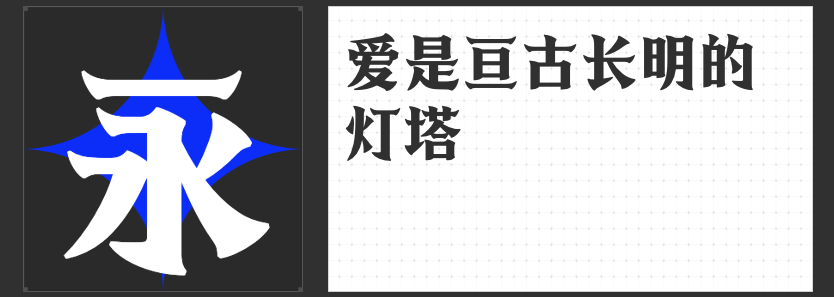
中秋佳节,让传统与现代交融的四款字体推荐
中秋佳节,自古以来便是中国人团圆美满的重要象征,也是展示传统文化魅力的最佳时刻。在这个特殊的节日里,选择一款既能体现传统韵味又能兼顾现代审美的字体,对于宣传设计来说至关重要。以下是四款适合用于中秋节宣传设计的字库字体推荐,每款字体都独具特色,适用于不同的设计用途。
1.造字侠热辣隶简
隶书作为一种历史悠久的汉字书写风格,以其工整中带有变化的特点著称。造字侠热辣隶简则是在传统隶书基础上加入了更多现代元素,使其更符合当今审美趋势。这种字体非常适合用于中秋节活动的邀请函、海报以及各种宣传材料的设计。无论是制作一张充满节日气氛的贺卡,还是一张吸引眼球的广告牌,热辣隶简都能以其独特的韵味增强作品的文化内涵。
2.造字侠朝凤宋简
宋体是中国最为常见且经典的印刷字体之一,它结构严谨、线条清晰,给人以庄重之感。造字侠朝凤宋简则是在宋体的基础上进行了现代化的改良,使其既保留了传统宋体的优点,又增添了新的活力。这款字体适用于需要展现传统文化底蕴的设计场合,如中秋主题的网站页面布局、电子贺卡及各类节日相关的出版物设计中,能有效地传达出节日的温馨与祝福。
这款字体以其苍劲有力的笔触而闻名,它结合了行书的自由与楷书的规范,给人一种大气磅礴的感觉。造字侠醉春风简繁 苍劲非常适合用于大型庆典活动的背景板设计、横幅标语制作以及各类户外广告宣传上。利用其独特的艺术效果,可以迅速吸引观众的目光,传达出浓郁的节日氛围。
4.高手兵克侠客体
这款字体以其独特的书写风格吸引了众多设计师的喜爱。它借鉴了古代书法大家的手笔,却又不乏时尚感。这种字体适用于创意性强、需要突出个性的设计项目中,比如中秋主题的社交媒体营销活动、创意礼品包装以及年轻人群体喜爱的节日纪念品设计等。侠客体能够帮助你的作品在众多设计中脱颖而出,成为令人难忘的经典之作。
综上所述,这四款字体各有千秋,可以根据具体的设计需求灵活运用,无论是在传统的纸质宣传品还是新兴的数字媒体平台上,都能让中秋佳节的宣传设计更加丰富多彩,既传承了传统文化之美,又不失时代气息。